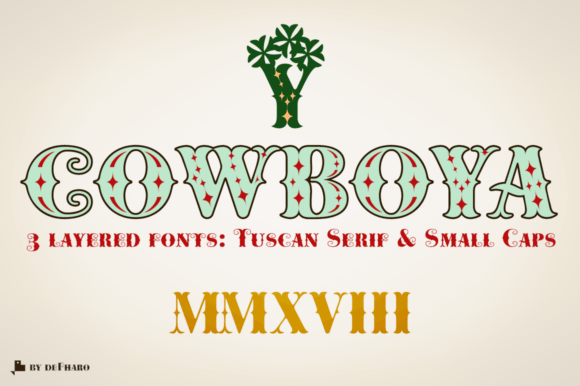
Cowboya
Ulasan Lengkap cowboya – Font Tuscan Serif yang Memukau
Jika anda mencari jenis huruf yang menggabungkan keanggunan sejarah dengan sentuhan modern, cowboya adalah pilihan yang tepat. Font ini menampilkan Tuscan serif yang tajam dan kontras tinggi, didesain dengan inspirasi modernisme serta small caps yang elegan. Dengan tiga varian warna yang dapat dilapisi, cowboya memberi efek multicolor yang menakjubkan pada judul dan headline.
Fitur Utama Cowboya
- Desain Tuscan Serif: Garis tebal dan tipis yang dramatis, memberikan nuansa klasik namun tetap segar.
- Versi 3 Layer: Dapat ditumpang satu sama lain sehingga menciptakan efek warna yang dinamis dan menarik.
- Inspirasi Sejarah: Terinspirasi dari judul film hitam di era 1950, "The House of the River" karya Frizt Lang.
- Elemen Dekoratif: Akun dan ornamen khas abad ke-19 Italia, cocok untuk tema sirkus, karneval, atau Far West.
- Modern & Techno: Rounding pada sudut tajam menghasilkan kontras yang lembut, memberi nuansa futuristik.
Manfaat Menggunakan Cowboya
Gunakan cowboya untuk:
- Judul film, poster, dan banner yang memerlukan kesan dramatis.
- Branding event bertema furthest west atau festival karneval.
- Website dan materi pemasaran yang ingin menonjolkan karakter vintage dengan sentuhan kontemporer.
- Desain grafis yang memanfaatkan lapisan warna untuk efek visual yang kuat.
Dengan kombinasi estetika klasik dan inovasi modern, cowboya menjadi pilihan sempurna bagi desainer yang ingin menciptakan visual yang tak terlupakan. Tidak hanya stylish, ia juga praktis dan fleksibel untuk berbagai platform digital.